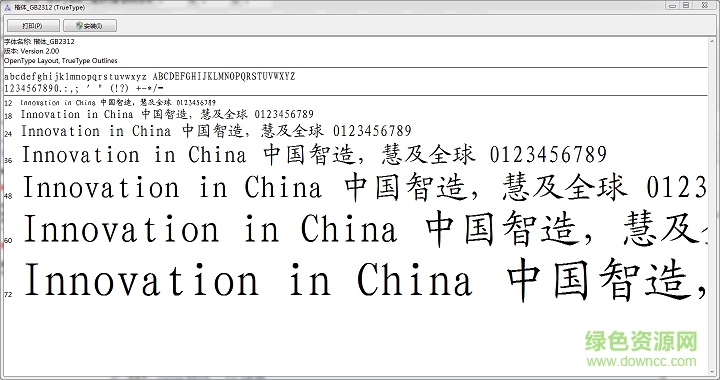
標(biāo)準(zhǔn)楷體字庫(kù)
標(biāo)準(zhǔn)楷體簡(jiǎn)字體是一款采用國(guó)家標(biāo)準(zhǔn)字符集的楷書字體,該字體結(jié)構(gòu)工整,線條過(guò)渡平穩(wěn),風(fēng)格質(zhì)樸,和范本一樣規(guī)矩方正,需要這款字體的小伙伴快來(lái)綠色資源網(wǎng)下載吧!